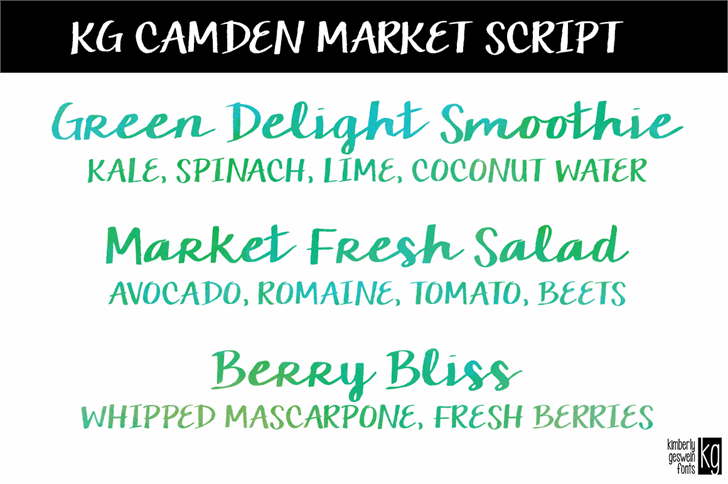
KG Camden Market Script font – Download Grátis
KG Camden Market Script é uma linda e divertida fonte script criada pela Kimberly Geswein em 2015. Ela traz características únicas de uma escrita feita à mão com traços de pincel, inspirada na águacolorística, resultando em um estilo descompromissado e fresco ideal para uso personalizado ou em projetos que valorizam a criatividade. Esta fonte é perfeita para ambientes gráficos vibrantes e vivazes como cartões de aniversário e calendários, design editorial de livros infantis, rótulos de vinhos, camisas com estampas e muito mais. Ela traz um toque agradável e único à sua próxima criação, prometendo deixá-la brilhar ainda mais. A fonte é gratuita para uso pessoal, mas se você está planejando usá-la em projetos comerciais, visite o site da Kimberly Geswein. Seja qual for o seu próximo projeto de design, essa fonte será um maravilhoso complemento a sua biblioteca de ferramentas.